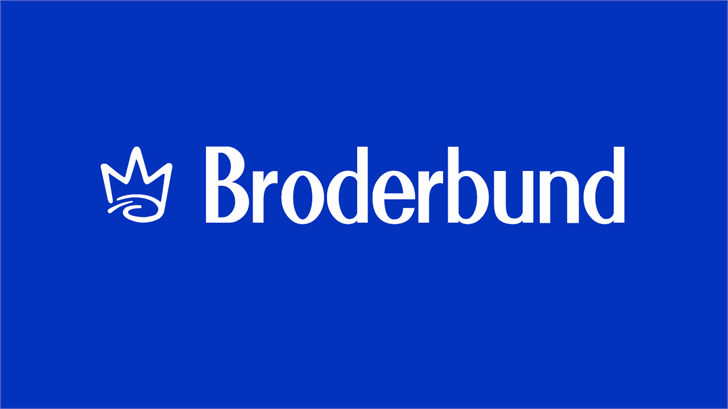
Blue Crown font – Download Grátis
A Blue Crown font foi criada por 538Fonts em 2015 para recrear a popular Broderbund font. Esta elegante e moderna fonte gira em torno de uma tipografia sans-serif, oferecendo um toque sofisticado que se adequa perfeitamente a muitos estilos de design gráfico. Sujeitiva e versátil, ela é particularmente interessante para designers de interface do usuário, ilustradores e criativos digitais em busca de uma fonte moderna com uma aparência atemporal. Com uma cor azul brilhante e um design clean, a Blue Crown traz à tona uma paleta de opções visuais versáteis e inovadoras para qualquer projeto gráfico.